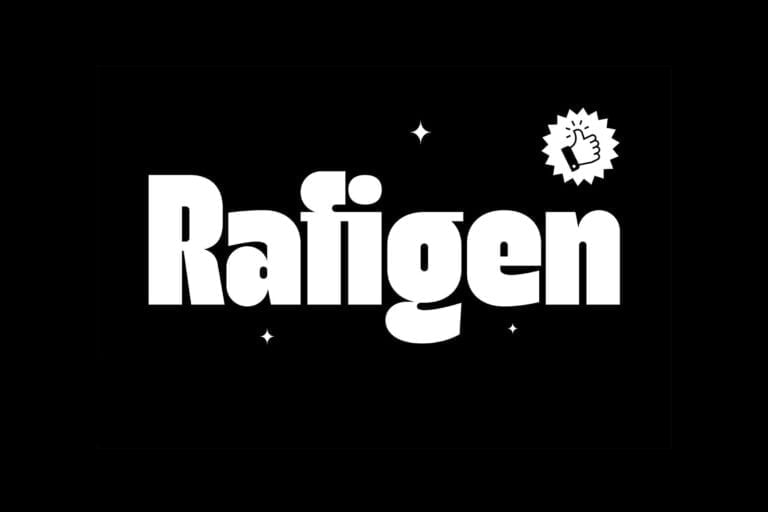
Rafigen Font là một kiểu chữ dày và vui tươi. Nó có hai phong cách khác nhau plain và slant.
Phông chữ này thực sự tuyệt vời giúp bạn thực hiện công việc sáng tạo dễ dàng và có thể sử dụng nó cho nhiều các thiết kế khác nhau như xây dựng thương hiệu, tiêu đề phim, bao bì, áp phích, tạp chí, website hoặc ứng dụng.
Với các nét chữ được thiết kế đậm, dày vì vậy nó được hiển thị tốt khi sử dụng ở kích thước lớn. Ngoài ra, một số ký tự được thiết kế với tính năng ink trap và một ký tự thay thế khác.